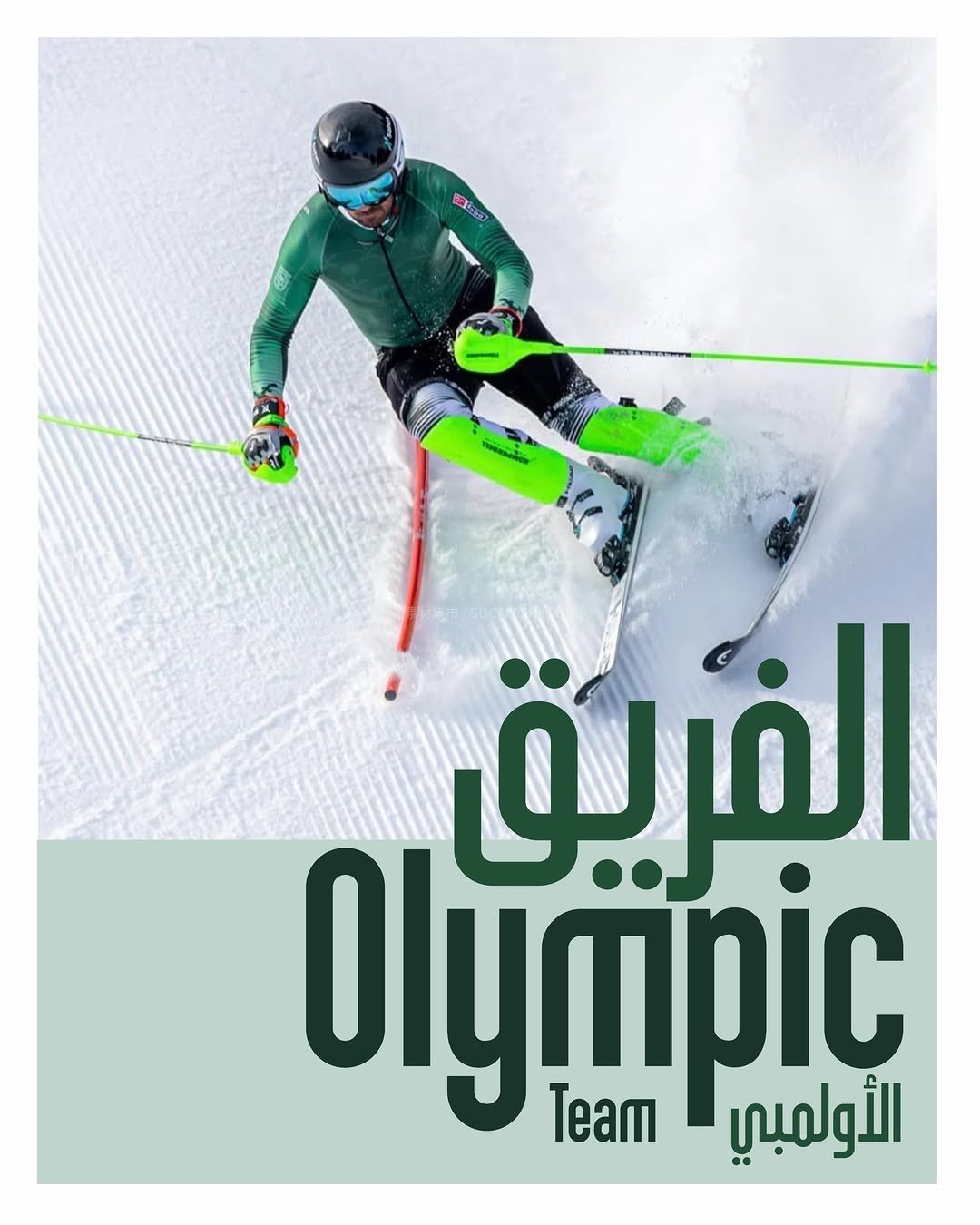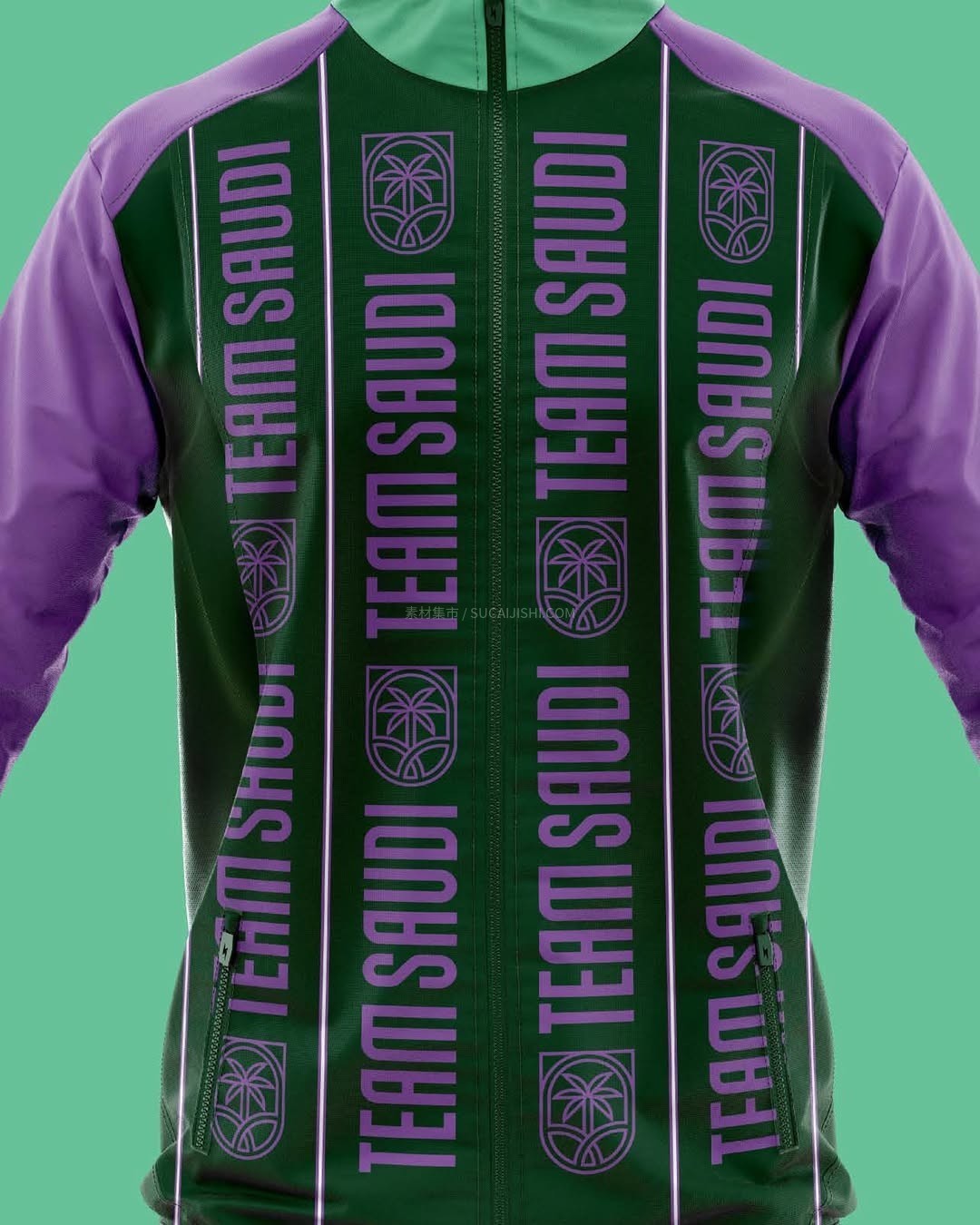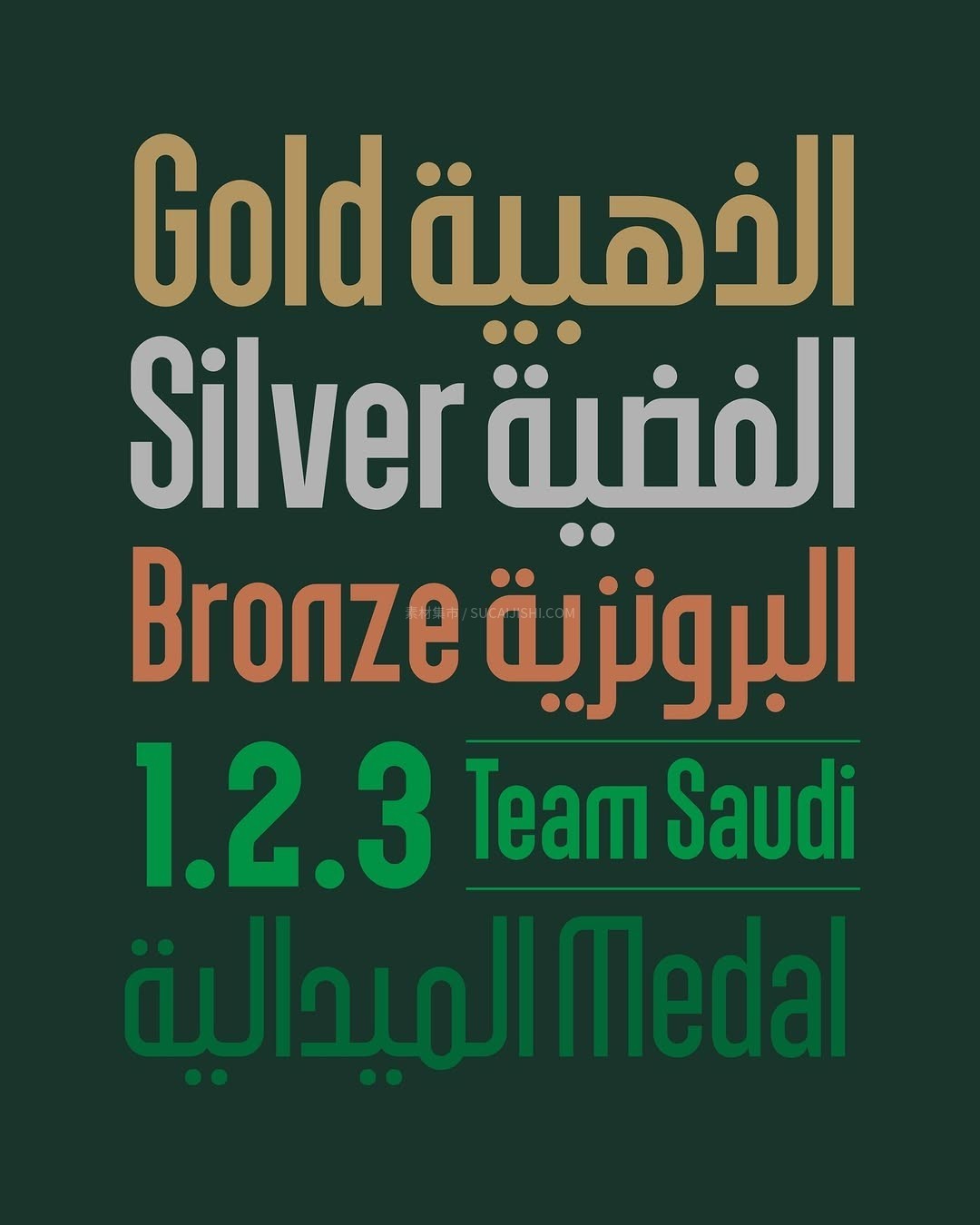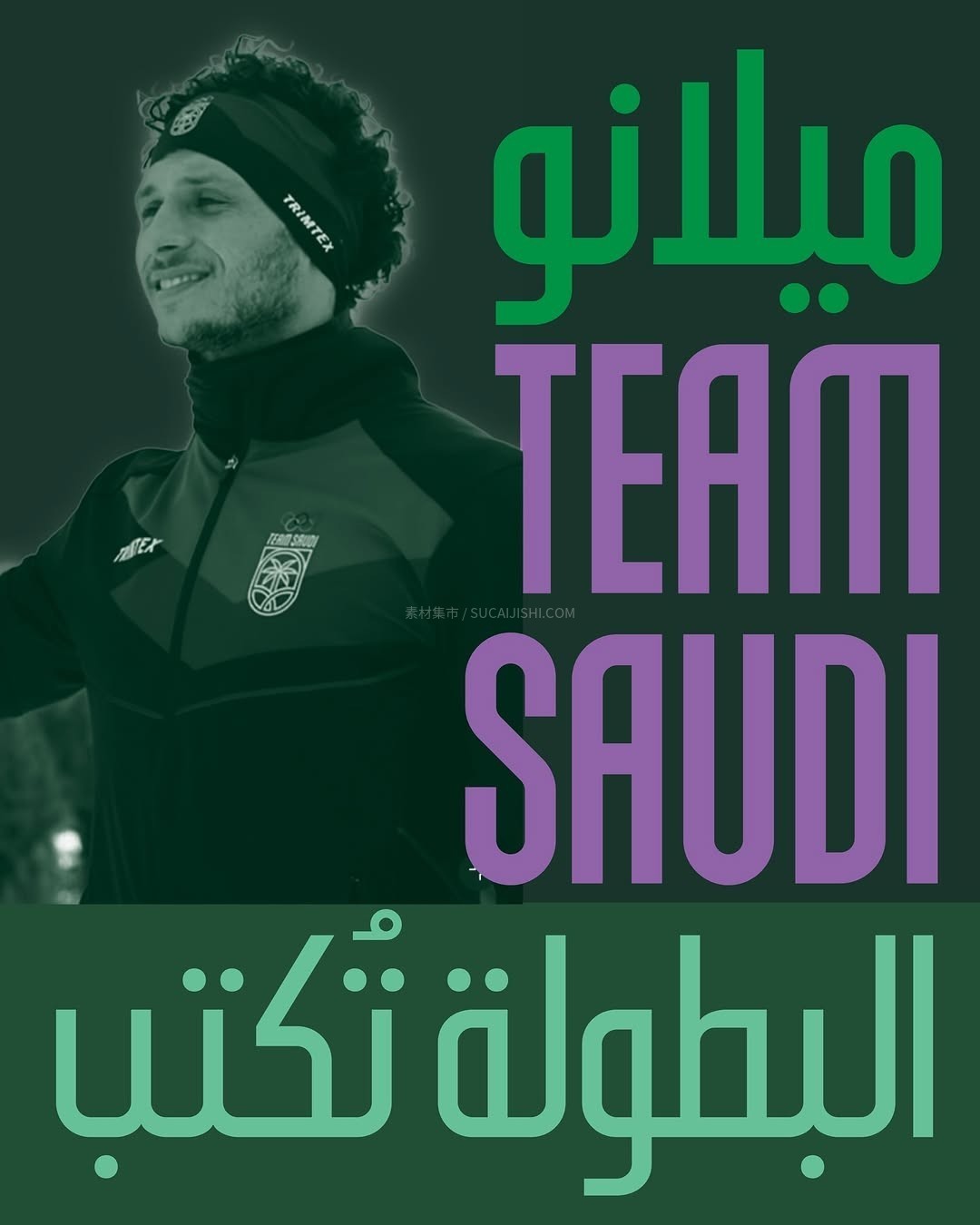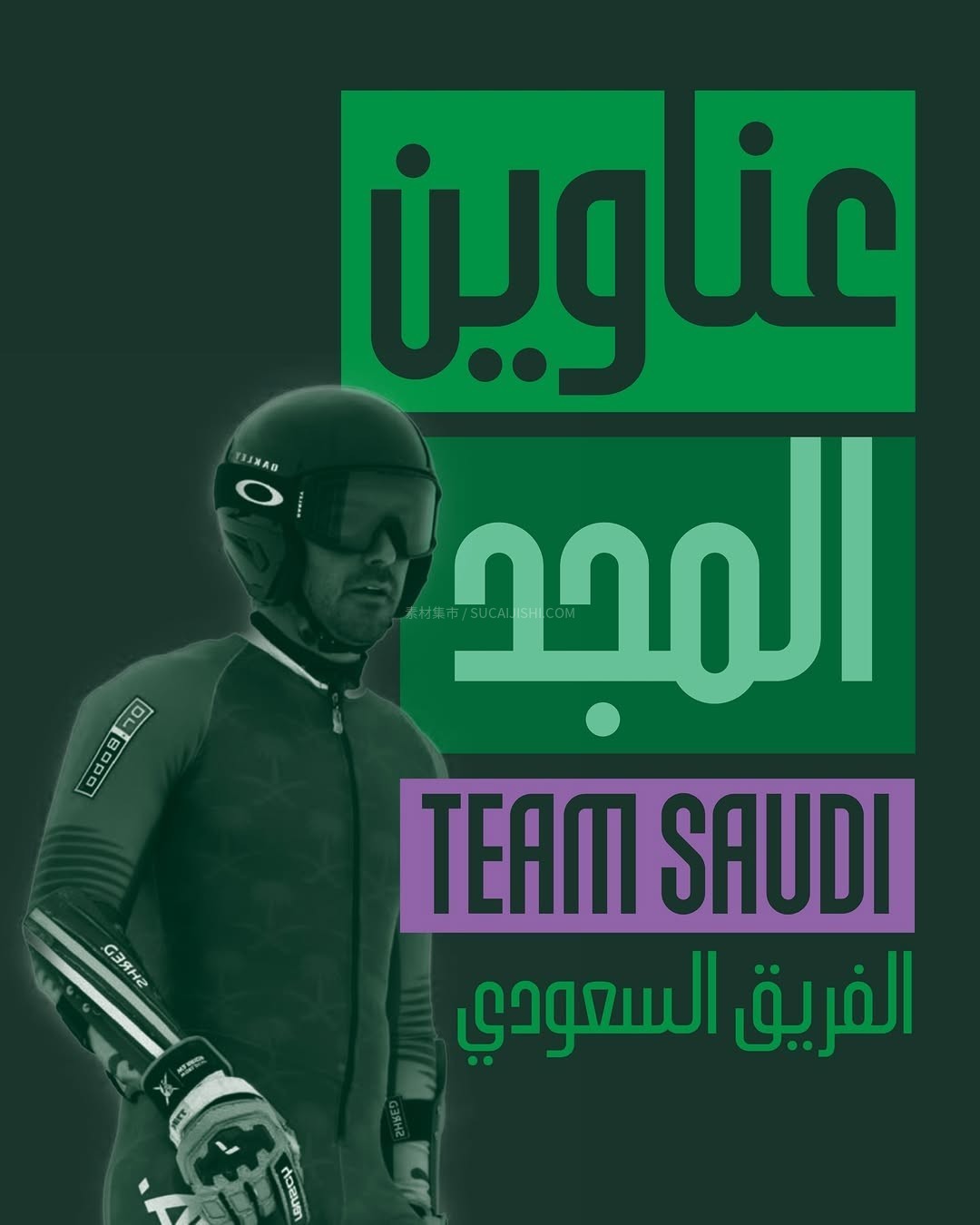
Team Saudi 沙特体育定制阿拉伯字体
Team Saudi 阿拉伯字体专为代表沙特出战国际赛事的官方代表团、奥林匹克及残奥委员会运动员,以及沙特国家足球队量身打造。字形设计完美融合了现代竞技的动感与传统阿拉伯文化的底蕴,极具视觉冲击力。无论是做赛事宣传、转播视觉还是周边设计,用它都能瞬间拉满力量感和高级感,轻松搞定纯正的中东风情排版!